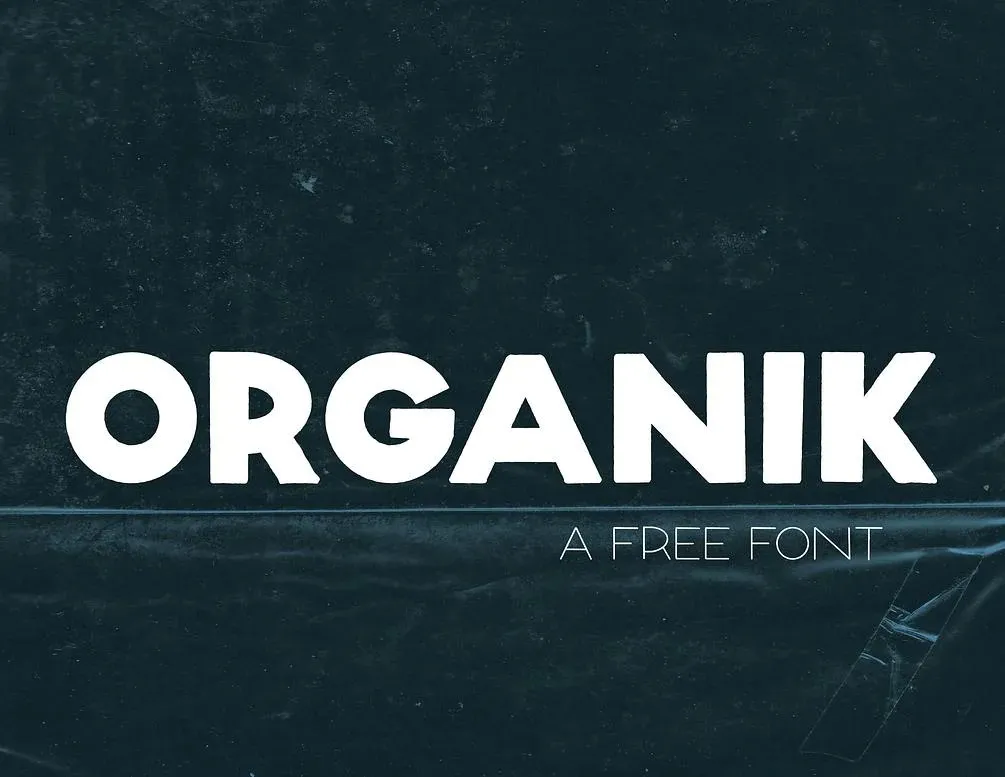
Aqui está uma descrição para a página de download da font ‘Organik Font’: Com seu toque natural de desenho à mão, essa fonte caiada é perfeita para adicionar um toque único e divertido às próximas criações de design. Ethan Schreiber criou esse lúcido e amigável tipo em maiúsculas, que traz uma sensação descontraída para qualquer projeto. Use a ‘Organik Font’ em suas postagens nas redes sociais, anúncios, embalagens ou até mesmo no planejamento de eventos — ela certamente enriquecerá seu próximo design. Nesse ambiente digital cada detalhe conta, e uma fonte como esta pode transformar um projeto apenas mediano em algo memorável. Seja para destacar o título de sua próxima peça publicitária ou para dar vida aos textos dos seus designs gráficos, a ‘Organik Font’ é perfeita para iluminar qualquer design que você esteja criando.